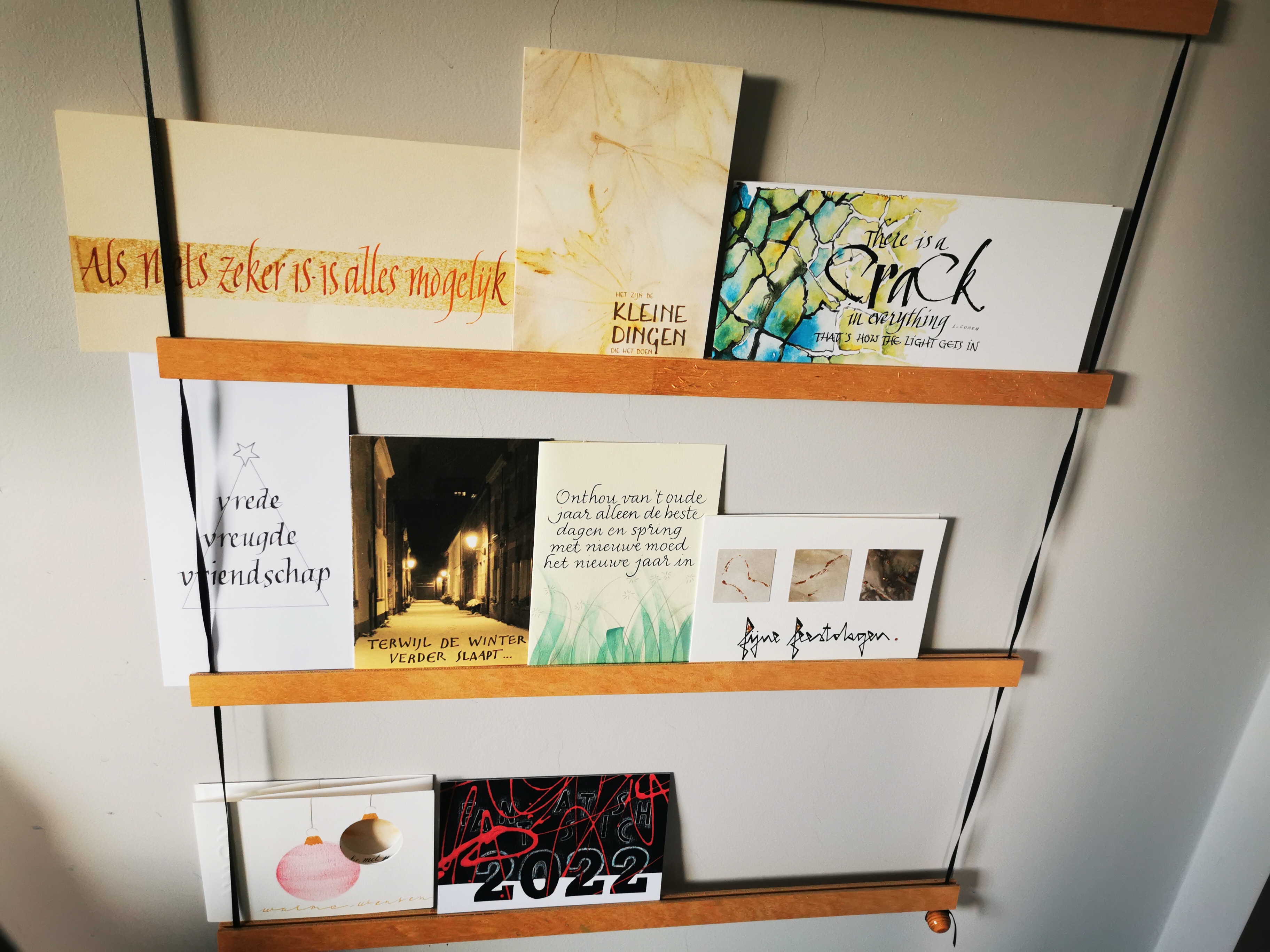
Het volgende werkje is geinspireerd door de kleuren van de herfst. Gecombineerd met de Marina Soria techniek, maakte ik deze leporello voor een verjaardag.
Today's work is a leporello (harmonica book) inspired by autumn leaves. I also used the 'Marina Soria technique'.
Love your autumn leaves book - and wow what a collection talented friends you have! Go well.
BeantwoordenVerwijderenMooie herfstkleuren, leuke kaart. Altijd een goede leidraad. Ben ook wel fan van Soria, maar het is een moeilijke techniek.
BeantwoordenVerwijderenVeel leuke kaartjes gekregen. Fijn zulke vrienden te hebben.
Weer helemaal jouw stijl in te herkennen.
BeantwoordenVerwijderenMooi hoor, de kleuren zijn prachtig.
Wauw, wat veel kaarten kreeg hij ook.
Leuk om die van mij er tussen te zien hangen.
Mooi Annick! Bij mij ook zo'n heerlijk gevuld rekje vol gekregen creatieve kaartjes. 😉
BeantwoordenVerwijderenlove how you displayed your holiday cards and I quite agree with Fiona that you have quite a talented circle of friends ... I'd have a hard time putting those away at the end of the season ... and the thought of creating a concertina book with them comes to mind
VerwijderenMooie kaarten! Van jou en van anderen!